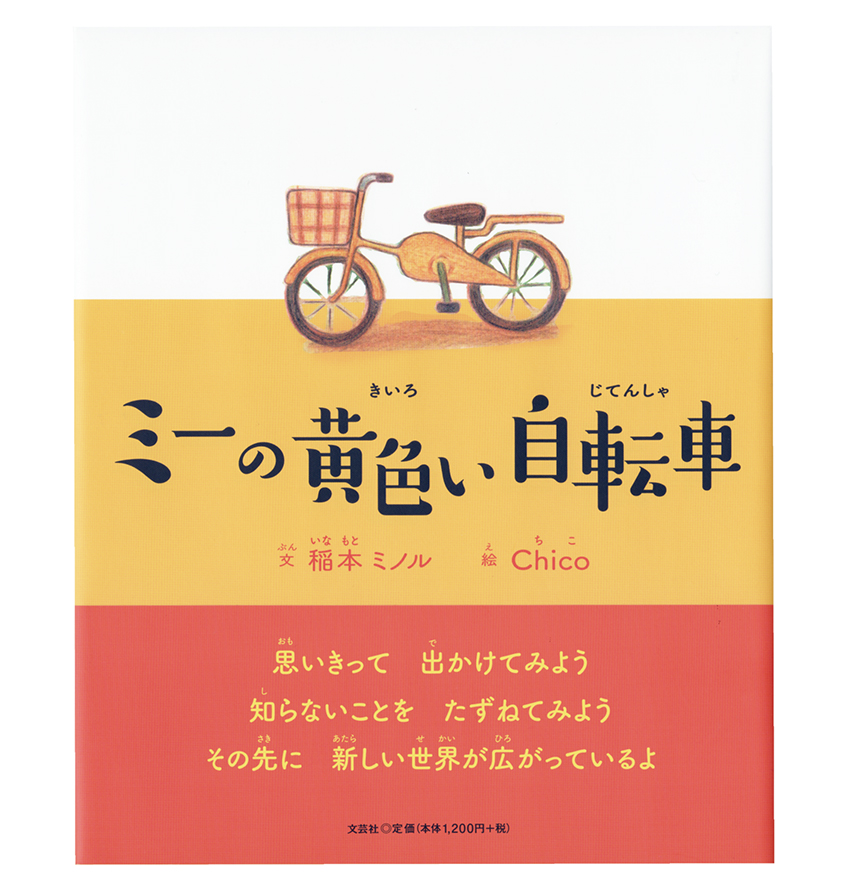
ミーの黄色い自転車
今回、紹介する絵本「ミーの黄色い自転車」の指すミーとは、お父さんに買ってもらった私の黄色い自転車という扱いで間違いなく、ミー=私でもあるが、ミーは少女の名前であって、ややこしいが自分の事を指すミーではなく、イヤミの事ではなく、ましてやBritney TOKYOの事でもない。
「ミーの黄色い自転車」はヘソプロダクションが文芸社から2018年4月上旬に刊行した絵本。文はヘソプロダクションの代表取締役・稲本ミノル氏でイラストはChico氏が手掛ける。
「イヤミのでもBritney TOKYOのでもないミーの黄色い自転車」の物語
お父さんに自転車を買ってもらったミー(私という意味ではない)は嬉しくて、早速、その自転車で出かけることに。道中、出会うものや目にするものは、ミー(イヤミでもない、Britney TOKYOでもない)にとってどれも新鮮に映る。
様々なものに疑問を投げかけるミーだが、気づくと夕方、海にたどりついていた。自然との触れ合いと、子どもらしい純粋な「なぜ?」「どうして?」の心が新しい世界を広げていくというメッセージが込められている。
ミーの黄色い自転車のタイトルのフォントはモリサワのすずむし
「すずむし」は、たくさんの墨を含んだ筆で書いたような、ふくよかで瑞々しい点画が親しみを感じさせる、かわいらしいデザインが特徴のデザインフォント。小さな字面に対して、あえて正方形にまとめない文字の設計がアンバランスながらも組上げたときに軽妙なリズムを生み出している。漢字、ひらがな、カタカナの字面の大きさの違いも相まって文字に動きを与えることができる。